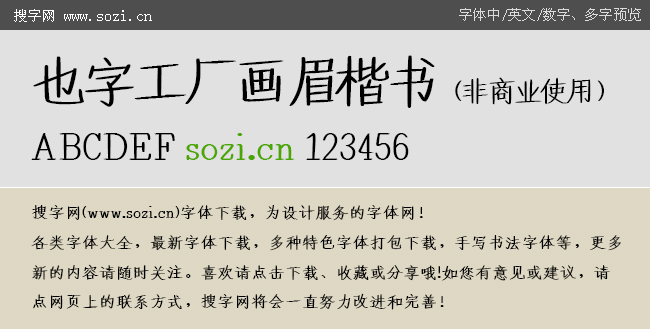
也字工廠畫眉楷書
搜字網(wǎng)給大家提供一款也字工廠畫眉楷書(非商業(yè)使用)中文字體下載,也字工廠畫眉楷書是一款楷書字體,字體簡潔大方,清晰明了。具有很好的視覺效果。適合應(yīng)用于藝術(shù)設(shè)計(jì)、平面宣傳設(shè)計(jì)、網(wǎng)頁設(shè)計(jì)、海報設(shè)計(jì)等應(yīng)用(此字體為個人非商用版,商用可以聯(lián)系:官方網(wǎng)址:https://yefont.com/home,聯(lián)系方式:13798980448)。